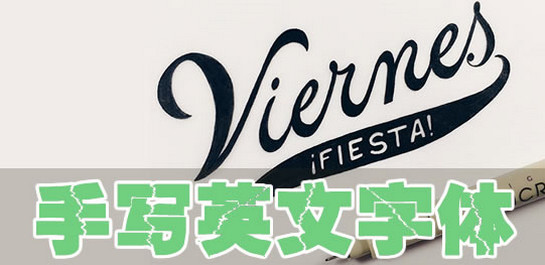
手寫字體打包一共包含了27款比較有特色的中文手寫體和英文手寫字體。這些字體在設(shè)計行業(yè)使用到的比較多一些。兼容多種系統(tǒng)環(huán)境,安裝方法簡單!歡迎在綠色資源網(wǎng)下載!
中文字體全部都是目前比較流行的,很好看,聊天的時候很有人氣哦!外文字體可以給老外留下很深的印象哦,全部都很對老外的胃口!
01-最酷最新英文手寫字體
02-收集近27款有特色的中文手寫體
流行的中文手寫字體:
流行的英文字體: